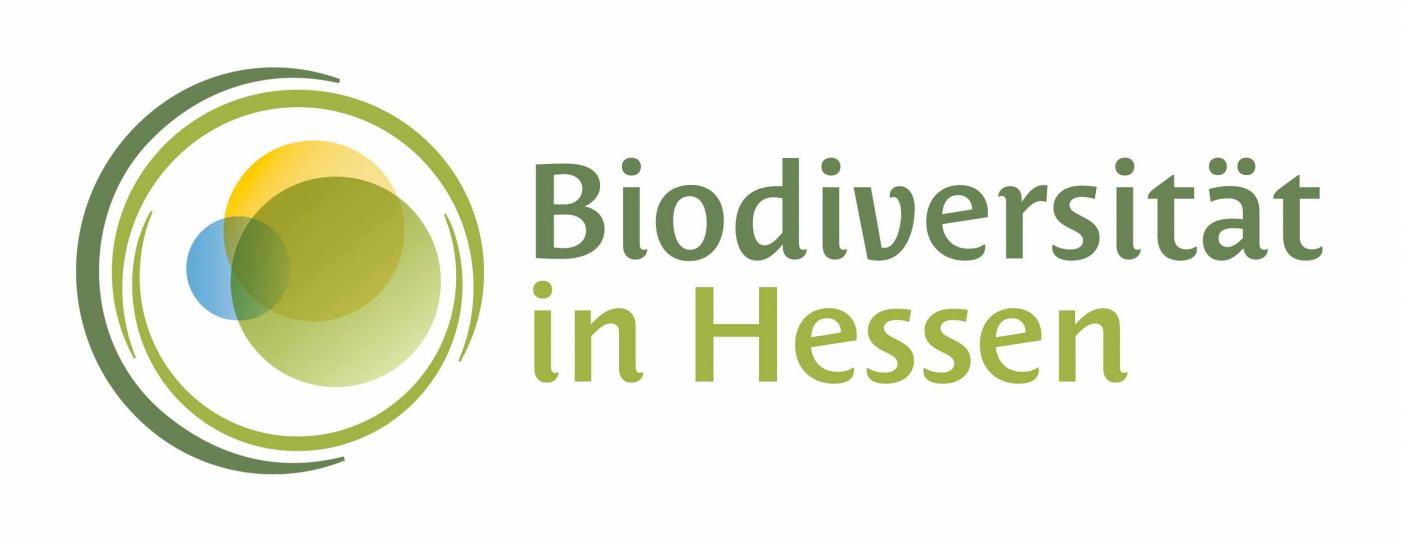
Suche passende Schrift für Vereinslogo
Die Schrift soll aktiv, offen, seriös, kompetent, freundlich und modern wirken. Ich denke an vertikaler Betonung, hohe x-Höhe, weiche Form und gut lesbar. Einsatzbereich Vogelkunde und Naturschutz.
Auf die Costa bin ich durch jenes Logo gekommen:
Ich ziehe die Monterchi wieder zurück, da habe ich die Frage völlig falsch gelesen. Stattdessen stelle ich die Cavolini in den Raum:
Aber die geht vielleicht schon zu sehr in Richtung Handgeschriebenes, erst recht dann die wohl Skriva und die Tekton:
Herzlichen Dank für Euer Engagement! Die Monterchi ist auch sehr schön. Ich suche eher noch etwas in Richtung Serifenbetont.
Die Costa mit 200 Euro liegt genau im Budget. Auf der Herstellerseite schreiben Sie, dass sie auch in kleinen Schirftgraden gut lesbar ist. Das heisst, man könnte Sie auch für Schulungsunterlagen und Präsentationsvorlagen wie Powerpoint einsetzten. Der einzige Nachteil ist, dass der Font nur über einen italic Schnitt verfügt.
Damit Du mit dem »einzigen« nicht Unrecht hast, steigere ich das mal und sage, das ist zwar der einzige Nachteil, aber nicht der einzigste: Sie hat nämlich, wenn ich mich nicht täusche, kein Versal-Eszett (früher oder später braucht man das). Zur Monterchi noch kurz: Du hast gesehen, dass es auch eine Monterchi Serif gibt? Und falls Du von der Monterchi ein Muster brauchst, kannst Du mir einen Text schicken, den ich dann nach Deinen Vorgaben setze.
Okay, dann hier erstmal ein paar Alternativen zur Costa welche auch für das weitere Erscheinungsbild (Schriftsatz) denkbar wären:
Mit Italics, ẞ und 50 % Rabatt aber disziplinierter
Mit Italics und ẞ
Mit Italics
@ Dieter. Danke für Deine Zuvorkommenheit. Ich habe mir den Schriftzug als Serife anzeigen lassen. Sie hat mich nicht ganz überzeugt.
Auf den ersten Blick passt Mariza und Shumo. Brauch jetzt gerade mal Zeit zum Verdauen. Und schaue mir alles in Ruhe an.
Da es hier um ein Logo geht, überzeugt mich das diesmal nicht. Wenn im Vereinsnamen kein ß ist, oder man den Namen eh nicht versal setzen will, sehe ich kein Problem :-?
Eine dazu passende Schrift für weitere Anwendungen sollte natürlich ein ẞ haben …
Richtig. Anscheinend habe ich schon wieder falsch gelesen. Das »Auf der Herstellerseite schreiben Sie, dass sie auch in kleinen Schirftgraden gut lesbar ist. Das heisst, man könnte Sie auch für Schulungsunterlagen und Präsentationsvorlagen wie Powerpoint einsetzten. Der einzige Nachteil ist, dass der Font nur über einen italic Schnitt verfügt« hatte ich voreilig so interpretiert, dass die Schrift entgegen der Eingangsfrage nun doch auch für normale Texte verwendet werden soll.
War vielleicht auch so gemeint, ich habe manches hier nur überflogen.
Dann sei mein Post so zu verstehen, dass beides ja nicht die gleiche Schrift sein muss … vor Allem, wenn’s nur am VE liegen sollte …
Nö, habe ich auch so verstanden und es spricht auch nichts dagegen, dass eine Wortmarke mit dem Rest des Erscheinungsbildes harmoniert. Im Gegenteil. Daher finde ich den Weg dazu auf eine Schriftfamilie oder -sippe zu setzen erstmal naheliegender und auch einfacher.
Uih, ich möchte mal sehen, wer da das Gegenteil behaupten würde …
Ich finde es meistens spannender, wenn das Logo nicht zum Einheitsbrei wird, sondern – in harmonischer Form – etwas heraussticht. Das kann man mit Schriftsippen erreichen oder mit Farbe oder Größe … oder mit einer anderen Schrift. Ich will nur sagen, dass das Fehlen des VE nicht unbedingt ein Ausschlusskriterium sein muss. Es sei denn, man will unbedingt alles in einer Schrift.
transportieren sollen und in welchem Umfeld die eingesetzt werden.
Danke. Das ist eine sehr hilfsbereite Community. Die Vereinszeitung, Schulungsunterlagen und die Präsentationen werden eigentlich nur in der Schweiz verwendet, deshalb wäre das Fehlen des VE kein Ausschlusskriterium. Mit einem italic Schnitt der Costa ist die Gestaltung begrenzt. Das verunsichert. Ich wäre gerne bei einer Schriftsippe geblieben. Ich habe mir auch Gedanken darüber gemacht, mit welcher Systemschrift sie allenfalls zusammenpassen würde. Evt. die Sego von Window? Als Mac Anwenderin muss ich die mir noch runterladen und genauer anschauen. Ich habe jetzt mein Konzeptpapier eingereicht. Und einige Schriften wie die Costa, Foco, Vista sans,  Muriza und die Shumo vorgeschlagen. Ich bin jetzt gespannt in welche Richtung es gehen soll.